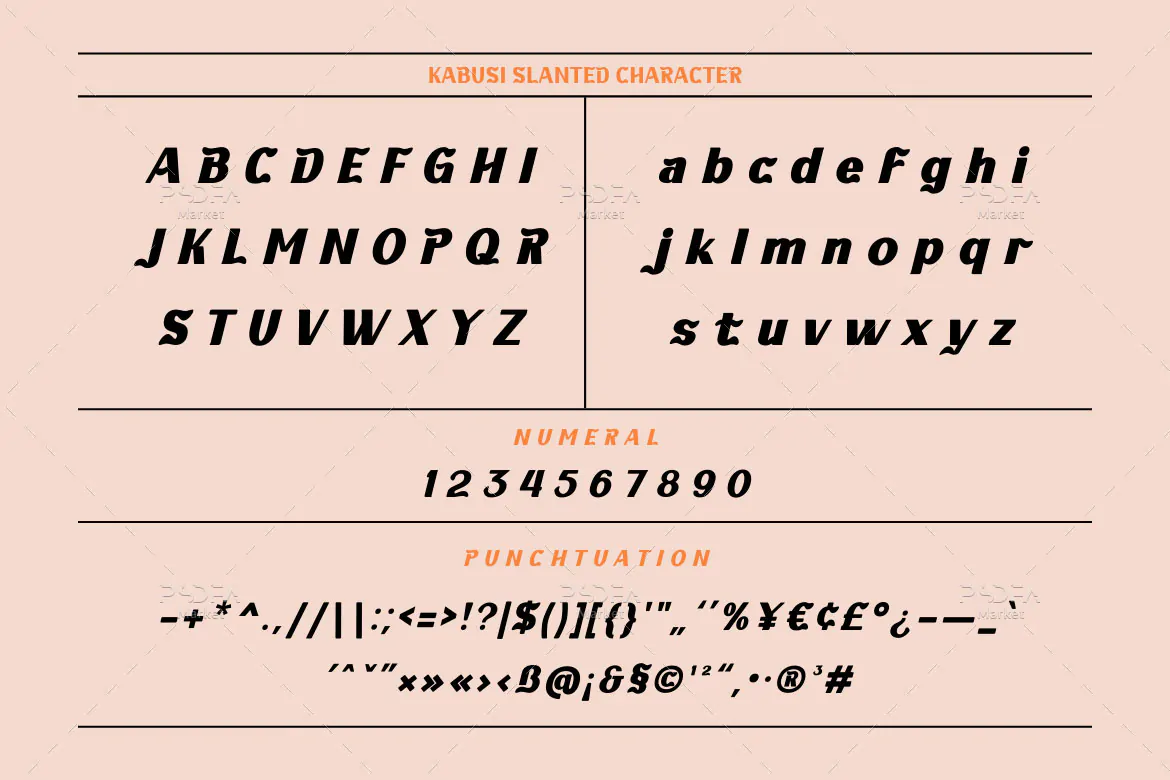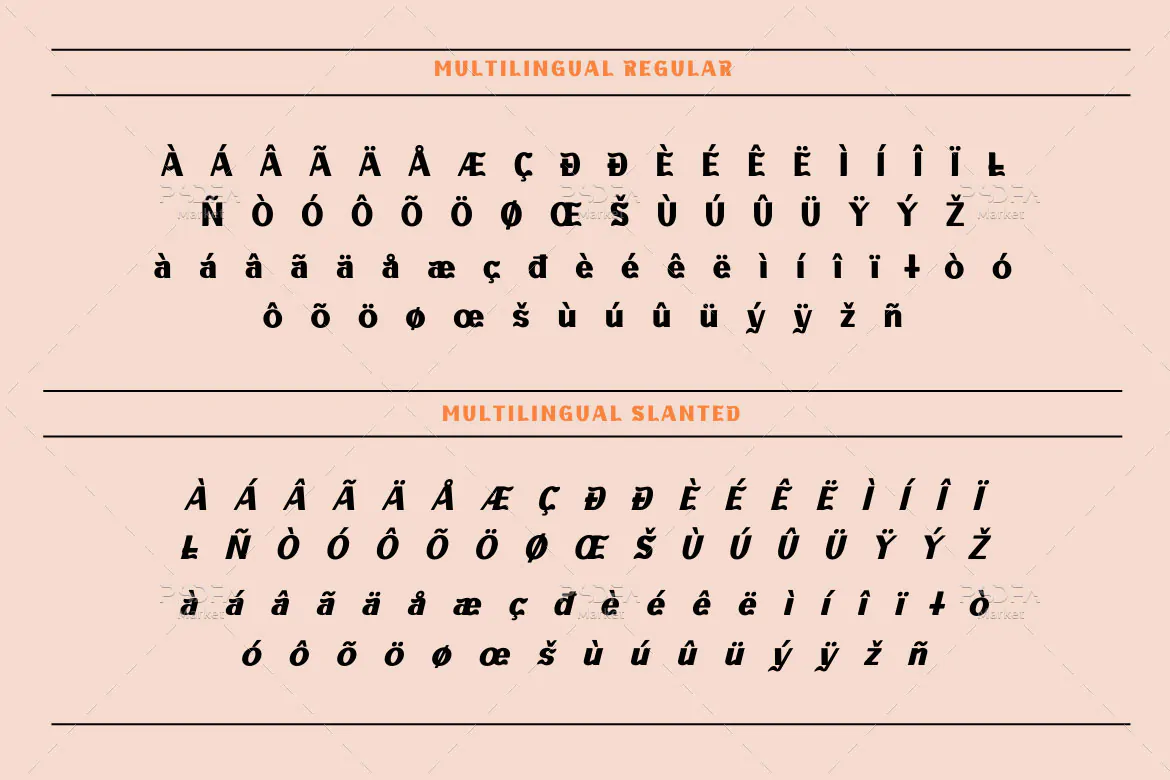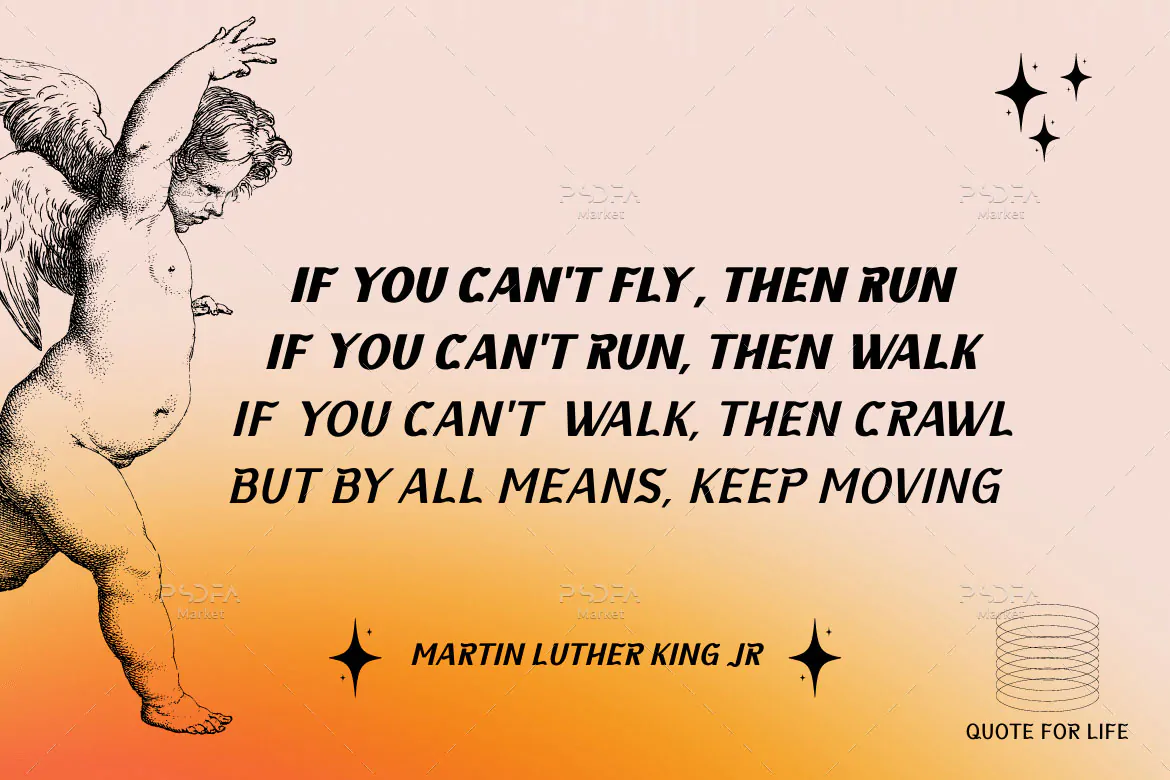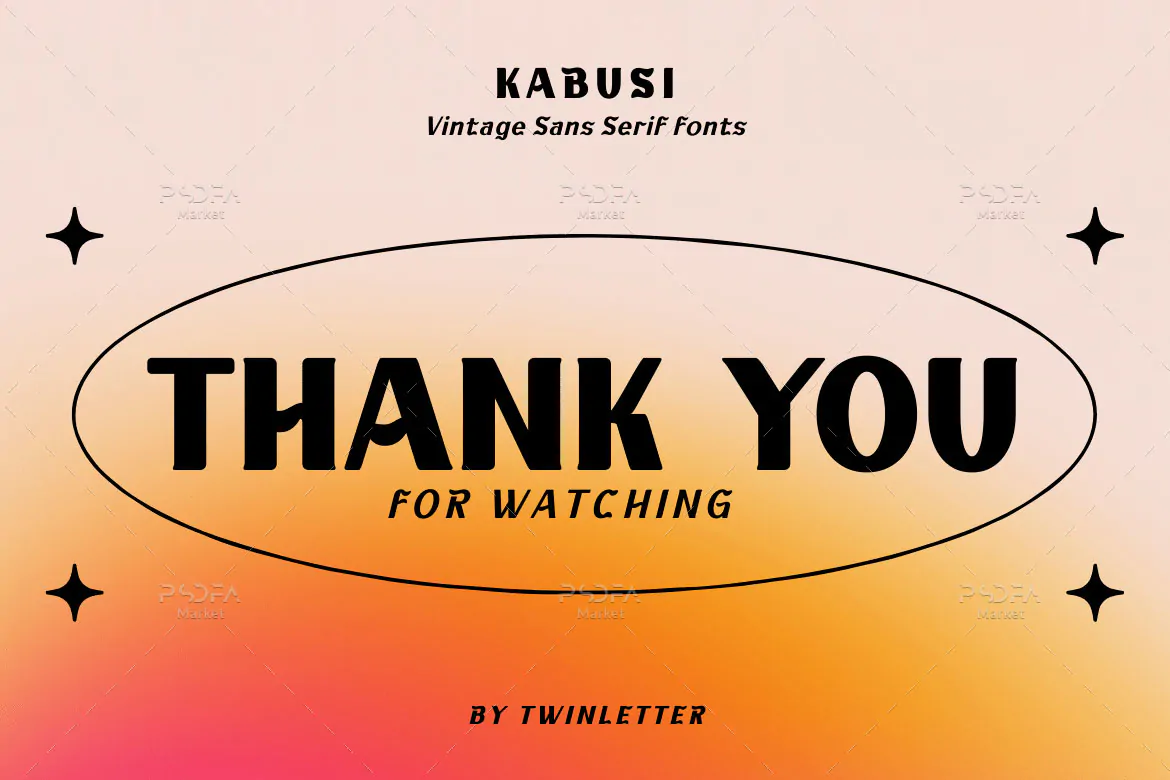
فونت سنس سریف کلاسیک Kabusi
فونت سنس سریف کلاسیک
فونت سنس سریف کلاسیک Kabusi یک قلم رترو و وینتج انگلیسی است که مناسب جهت استفاده در طرح و پروژههای گرافیکی مختلف میباشد. فونت Kabusi با 18 وزن مختلف طراحی شده است که میتوانید از آن در طراحی انواع پوستر، کارت ویزیت، بروشور، تراکت، بنر، تقویم، کتاب و مجلات، روزنامه، لوازم التحریر، بسته بندی محصولات و … استفاده کنید.